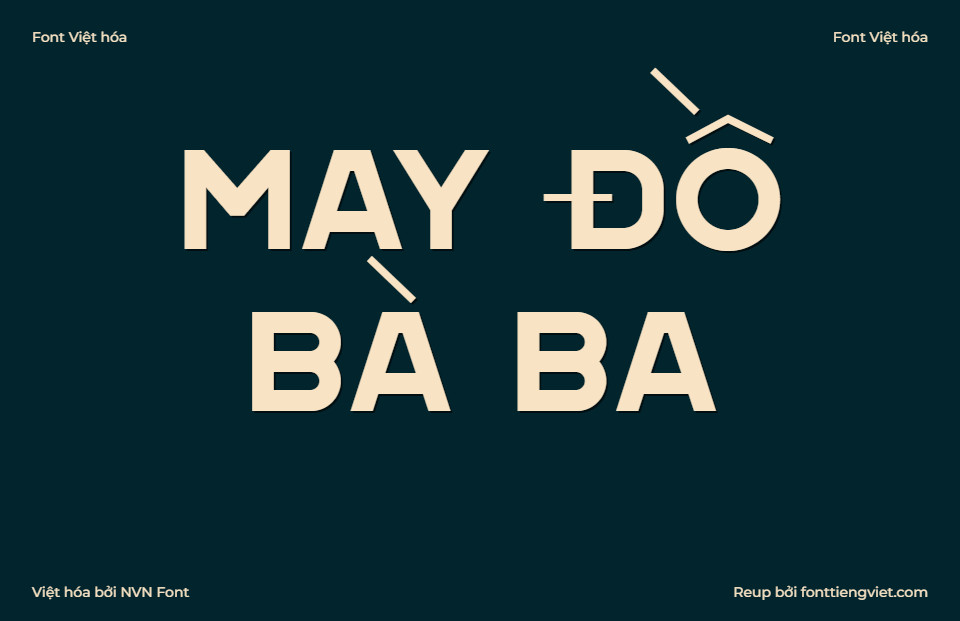
Font Việt hoá NVN Wichita Vinage Regular
Font Việt hoá NVN Wichita Vinage Regular – Nét đẹp hoài cổ cho mọi thiết kế
Giới thiệu về Font Việt hoá NVN Wichita Vinage Regular
Trong thế giới thiết kế đồ họa hiện đại, việc tìm kiếm một bộ Font Miễn Phí có khả năng truyền tải cảm xúc hoài cổ nhưng vẫn giữ được nét thanh lịch là điều vô cùng cần thiết. Font Việt hoá NVN Wichita Vinage Regular chính là câu trả lời hoàn hảo cho những ai đang theo đuổi phong cách Vintage. Đây là một bộ phông chữ được tinh chỉnh kỹ lưỡng về dấu tiếng Việt, giúp các nhà thiết kế tại Việt Nam dễ dàng ứng dụng vào các dự án truyền thông mà không lo lỗi hiển thị. Với các đường nét mạnh mẽ, dứt khoát nhưng không kém phần mềm mại ở các góc bo tròn, bộ font này mang đến một luồng gió mới cho thị trường phông chữ Việt hóa hiện nay.
Đặc điểm nổi bật của Font Việt hoá NVN Wichita Vinage Regular
Phong cách thiết kế đậm chất cổ điển
Font Việt hoá NVN Wichita Vinage Regular sở hữu cấu trúc chữ cân đối, lấy cảm hứng từ các bảng hiệu quảng cáo phương Tây thế kỷ trước. Sự kết hợp giữa độ dày vừa phải và các chi tiết giả cổ giúp bộ chữ này tạo nên chiều sâu cho nội dung. Khi sử dụng trong thiết kế, nó không chỉ đơn thuần là các ký tự mà còn là một tác phẩm nghệ thuật, gợi nhắc về những kỷ niệm xưa cũ đầy hoài niệm.
Khả năng ứng dụng linh hoạt trong giáo dục và đời sống
Đối với các em học sinh và thầy cô giáo, việc sử dụng bộ font này trong các bài thuyết trình hay thiết kế báo tường sẽ giúp nội dung trở nên sinh động và thu hút hơn. Phông chữ này cực kỳ phù hợp cho các tiêu đề lớn, banner sự kiện trường học hoặc các loại thiệp mời tri ân. Tính đọc hiểu cao và sự rõ ràng của từng mặt chữ giúp người xem dễ dàng tiếp nhận thông tin mà không bị mỏi mắt.
Cách sử dụng Font Việt hoá NVN Wichita Vinage Regular hiệu quả
Phối hợp màu sắc và bố cục
Để làm nổi bật vẻ đẹp của Font Việt hoá NVN Wichita Vinage Regular, bạn nên kết hợp với những gam màu trầm như nâu đất, vàng nghệ hoặc xanh rêu. Việc đặt phông chữ này trên các nền giấy kraft hoặc hình ảnh có độ nhiễu nhẹ sẽ tạo ra hiệu ứng thị giác cực kỳ ấn tượng. Đừng quên điều chỉnh khoảng cách giữa các chữ (kerning) để đạt được sự cân bằng tối ưu nhất cho tổng thể thiết kế của bạn.
Kết luận về bộ phông chữ độc đáo